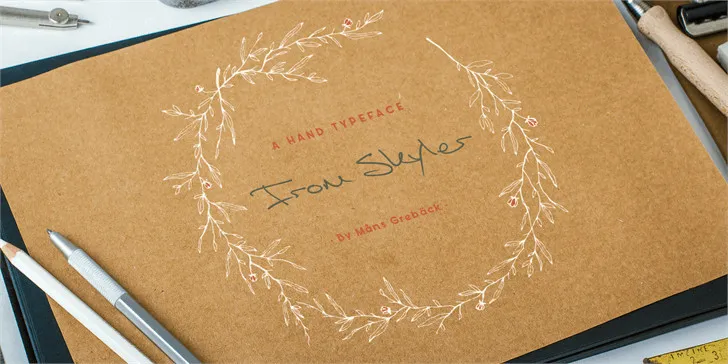
A partir do Skyler Font, a fonte escrita à mão que você está procurando, oferece uma experiência autêntica e emocional, perfeita para criar mensagens memoráveis e emotivas. Ideal tanto para os designers de sites quanto para aqueles que precisam de um recurso gráfico mais personalizado em publicações digitais. Måns Grebäck criou esta fonte cuidadosamente, fornecendo uma escrita à mão envolvente e autêntica para você usar na sua próxima criação visual. Com seu design suave e autêntico, a Skyler Font é perfeita para adicionar um toque único às suas projetos de design. Seja em aplicativos móveis ou no desktop, essa fonte escrita à mão oferece uma combinação única de facilidade de uso e qualidade visual incrível. Para os criadores que buscam algo mais pessoal na criação digital, a Skyler Font é um ótimo recurso. Visite o site oficial do designer para adquirir as licenças comerciais necessárias ou se tiver alguma dúvida, o FAQ pode ajudar com todas as suas perguntas.
Designer: Måns Grebäck